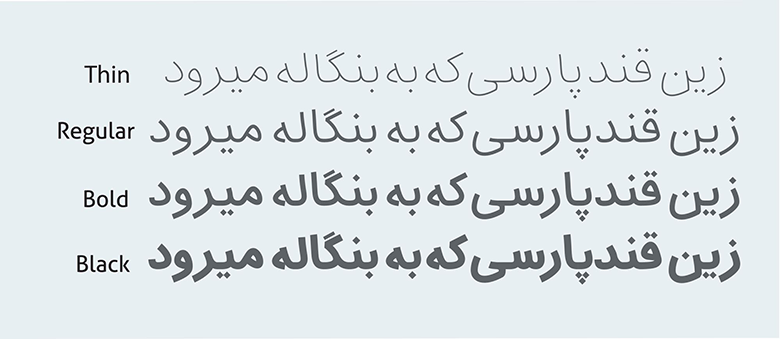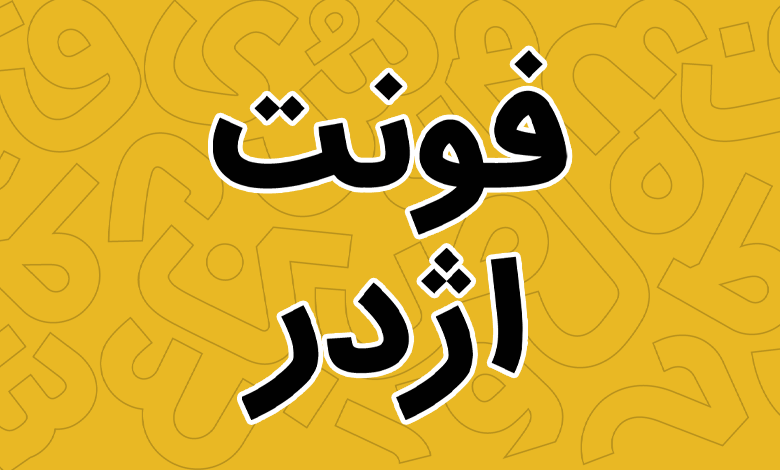
فونت اژدر (Azhdar)
مصطفی اوجی؛ خوشنویس و طراح گرافیک شیرازی، فونت اژدر را بر پایه فونت نسخ ایرانی طراحی نموده است. این فونت منولاین (با ضخامت یکسان) در ۴ وزن نازک، معمولی، بولد و سیاه طراحی شده است که دارای فرمتهای ttf، woff و woff2 با قابلیت پشتیبانی از اعداد فارسی و انگلیسی است.
معرفی و بررسی فونت اژدر (Azhdar)
فونت اژدر از زبانهای فارسی، انگلیسی و عربی بهصورت کامل پشتیبانی میکند و در بسته این فونت میتوانید به فونتهای با اعداد تمام فارسی، نسخه بدون اعداد انگلیسی و نسخه ترکیبی از اعداد انگلیسی و فارسی دسترسی داشته باشید که برای همین منظور به نسخهای مناسب برای استفاده از وب فونت در سایتها نیز تبدیل شده است.
یکی از مزایای فونت اژدر رعایت خطوط کرسی فوقانی و تحتانی در آن است که فواصل بین سطرها را در هر یک از وزنهای نازک تا سیاه با نظم کامل و بهصورت کامل یکدست به نمایش میگذارد. فواصل افقی نیز به شکلی طراحی شده که در اندازه فونت با ابعاد کوچک تا بسیار بزرگ نیز رعایت شود. از این فونت متن میتوانید برای وب، طراحی اپلیکیشن در موبایل و مطبوعات نیز استفاده کنید که خوانایی مناسبی به متن میدهد.
مزایای فونت نسخ اژدر فارسی
فونت اژدر پر از منحنیهای خاص و گاها شکسته در برخی حروف است که با زاویه مناسبی که این شکستگیها دارند، شکل بهخصوصی به این فونت داده است. همین شکستگیها که در برخی حروف کلیدی همچون «ج، چ،ح، خ، ع، غ، ی» دارد، خوانایی متن را افزایش خواهد داد و در متنهای بلند موجب سردرگمی کاربر نخواهد شد. شکستگیهای این حروف زیاد تند نیستند.
مزیت اصلی این فونت در استفاده تبلیغات است. کنراست بالای آن و از سوی دیگر شکل کلاسیکی که دارد میتواند روی برندینگ و زیبایی متن تاثیرگذار باشد. از دیگر مزایای این فونت میتوان به موارد زیر اشاره کرد:
- مناسب برای متن، مطبوعات، تبلیغات، طراحی و گرافیک
- فونت فارسی بر پایه نسخ ایرانی و مناسب برای متن و تبلیغات
- هماهنگی عالی و کامل با فونتهای لاتین San Serif
- دارای ۴ وزن مختلف Thin، Regular، Bold و Black
- پشتیبانی از سه زبان فارسی، عربی و انگلیسی همراه با اعراب کامل
- رعایت کامل فواصل و خطوط در بخشهای فوقانی، تحتانی و شکستگیهای فونت
فونت Azhdar در تمامی حروف دارای یک زاویه خاصی به شکل مورب است که استایل خاصی به آن داده است و باعث میشود کلمات به شکل منظمی در کنار هم چیده شوند. در مقابل نقطهگذاری حروف نیز به شکل کاملا چهار گوش و تیز هستند که تضاد آنها با منحنیهای حروف هم خوانایی بهتری به فونت میدهد و هم اینکه این تضاد شکل زیباتری را ایجاد کرده است.
اگر بهدنبال یک فونت فارسی متن سنس مناسب برای تبلیغات و همچنین استفاده برای وب هستید، پیشنهاد میکنیم از این فونت در پروژههای خود استفاده کنید. میتوانید فونت اژدر را با دیگر فونتها که دارای استایل ضخیمتری همچون لاله زار هستند، به صورت ترکیبی استفاده کرده و یک خروجی عالی از آن داشته باشید.
فونت اژدر همانطور که گفتیم توسط مصطفی اوجی طراحی شده و امین عابدی توسعه و ساخت این فونت را به سرانجام رسانیده است. این فونت در آذر ۱۴۰۱ به نسخه ۱.۱ بهروزرسانی شده و مشکلاتی که در این فونت وجود داشته برطرف شده است.